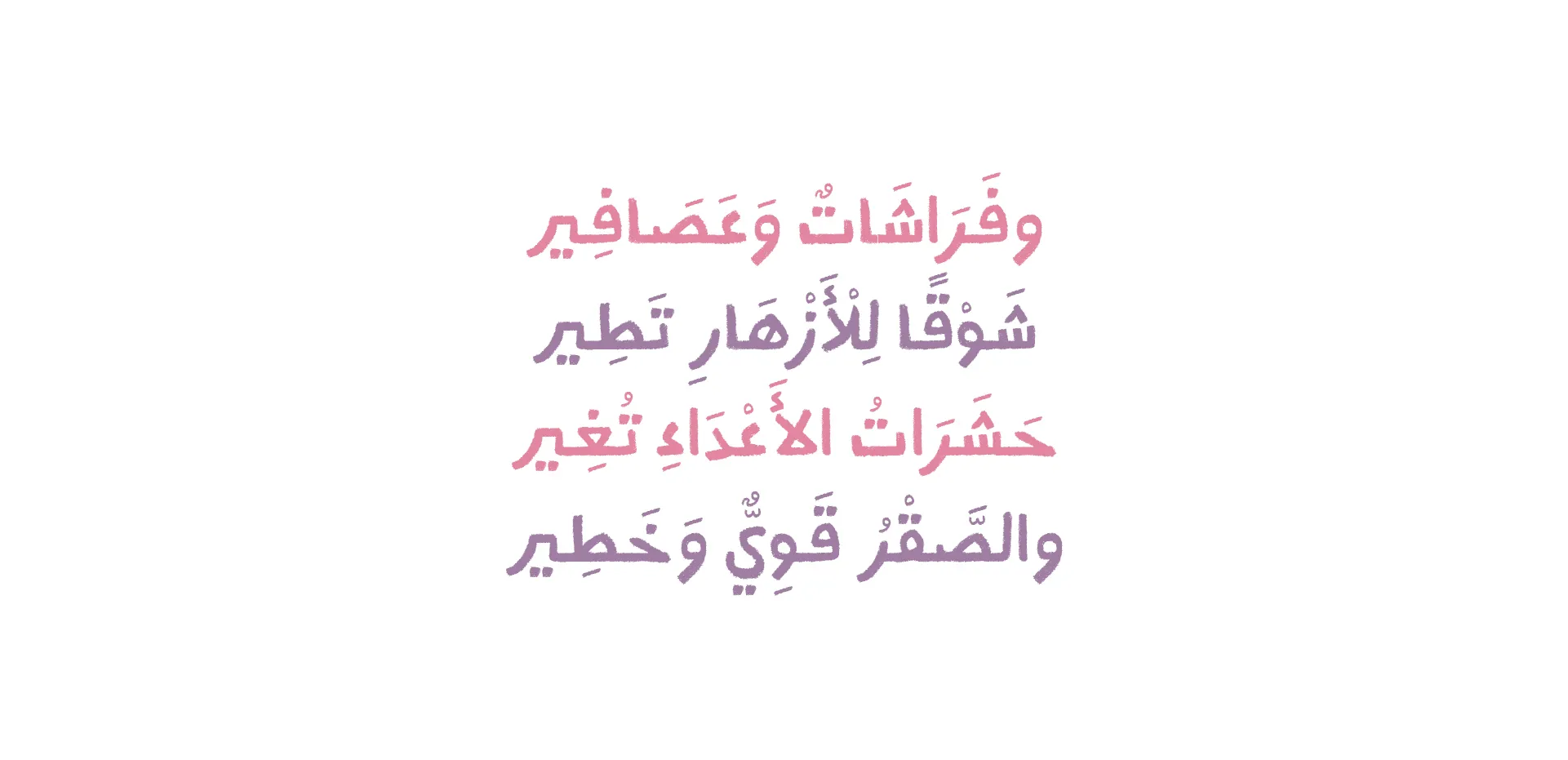
Tabshoor Typeface
Classification
Display handwritten
Tabshoor means crayon in Arabic. It is a cute typeface, hand-drawn with a crayon. Tabshoor project began as an experiment to design a textured typeface and ended up with a digital typeface resembling the shape of letters written naturally with a crayon on paper. The characters have coarse details and small spaces, due to the nature of the crayon. Tabshoor is suitable for cute designs and writings in children's books, posters, and headlines, and goes well with drawings and illustrations.
خط طبشور
التصنيف
عرض يدويّ
طبشور خط  يدوي طفولي وعفويّ، مرسوم بقلم طبشوريّ؛ كما يوحي به اسمه.بدأت صناعة طبشور كتجربة تصميم خط يحتوي على خامة، وانتهت بخط رقمي بزوايا وانحناءات شبيهة بشكل حروف مكتوبة طبيعيًّا بقلم طبشور على ورق. نسبة لنوع القلم، رسم الحروف يحتوي على الكثير من التفاصيل الخشنة والفراغات الصغيرة. يناسب طبشور التصاميم والكتابات اللطيفة، وتشمل استخدامات الخط كتب الأطفال، والملصقات، والعناوين، والتصاميم المتضمنة رسومًا يدويَّةً وإيضاحية.
تفاصيل الخامة
Texture details
حروف مقرونة
Ligatures
ضبط المسافات
Kerning
بدائل سياقية
Contextual alternates